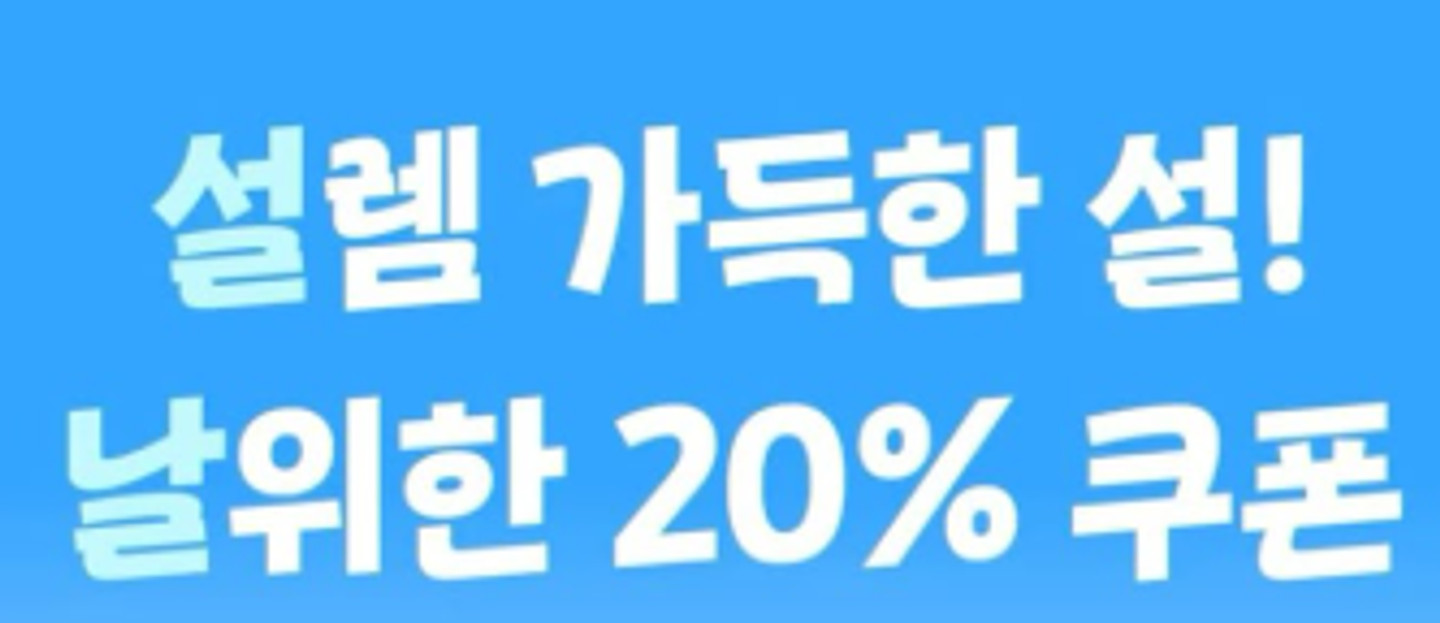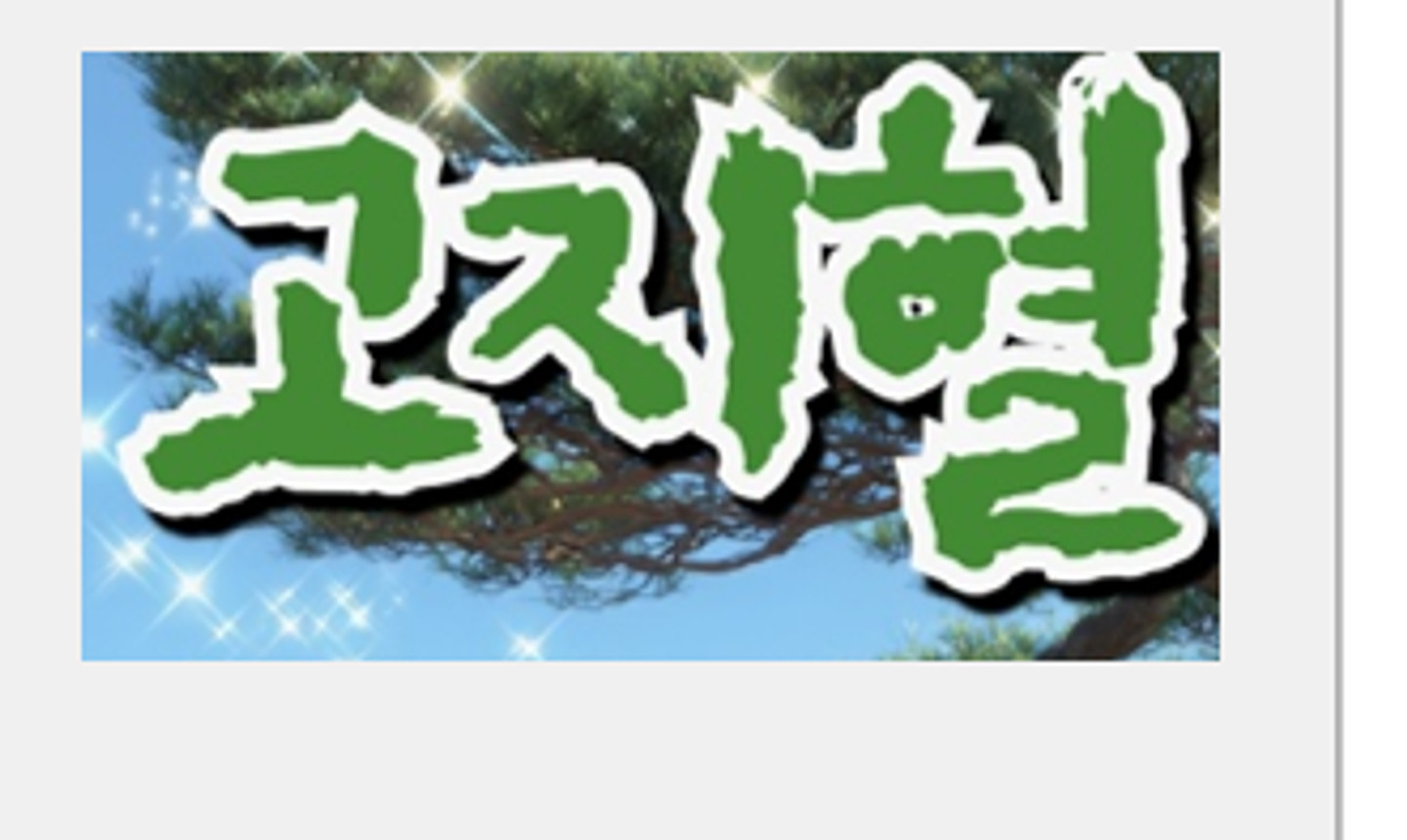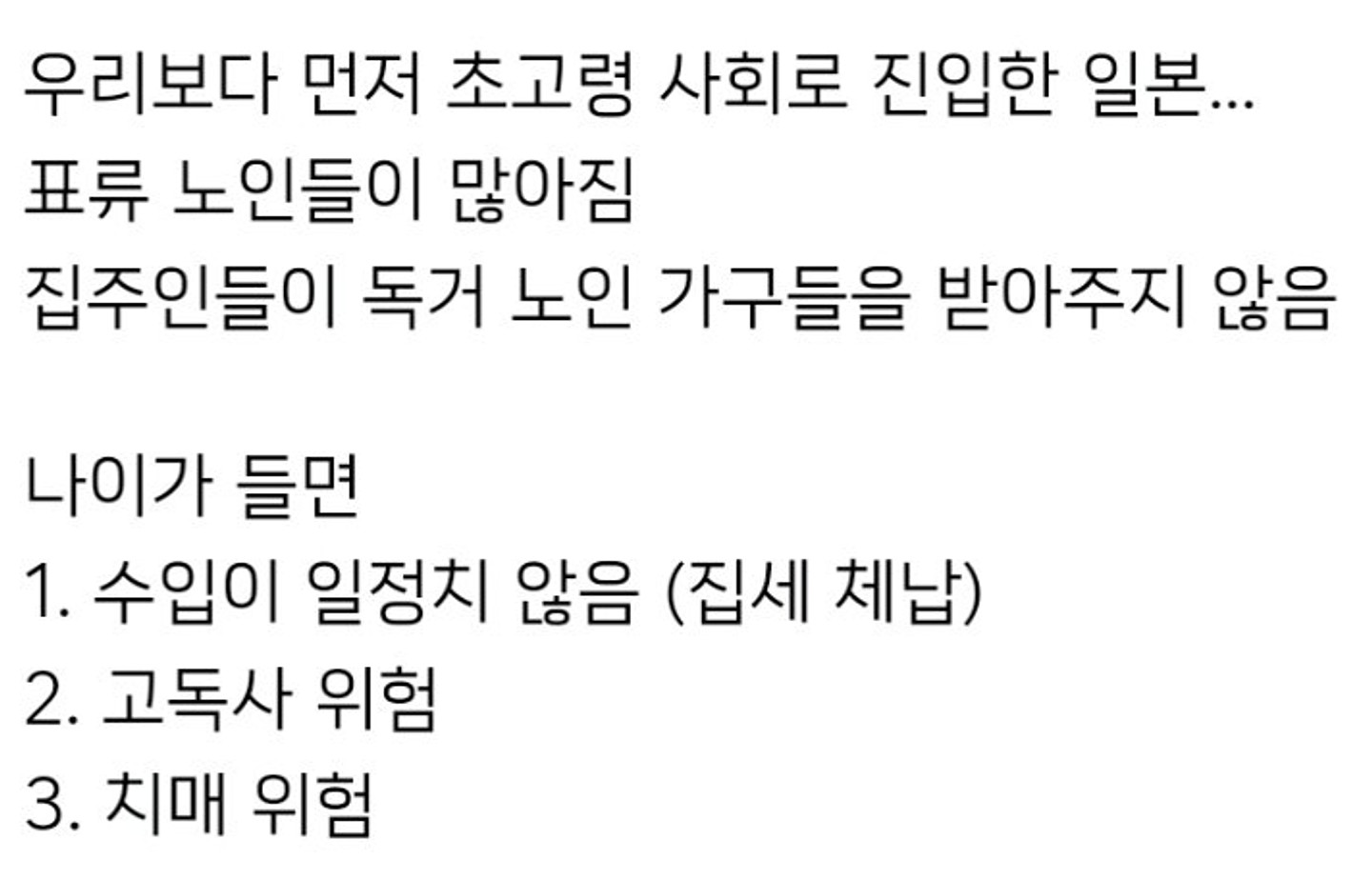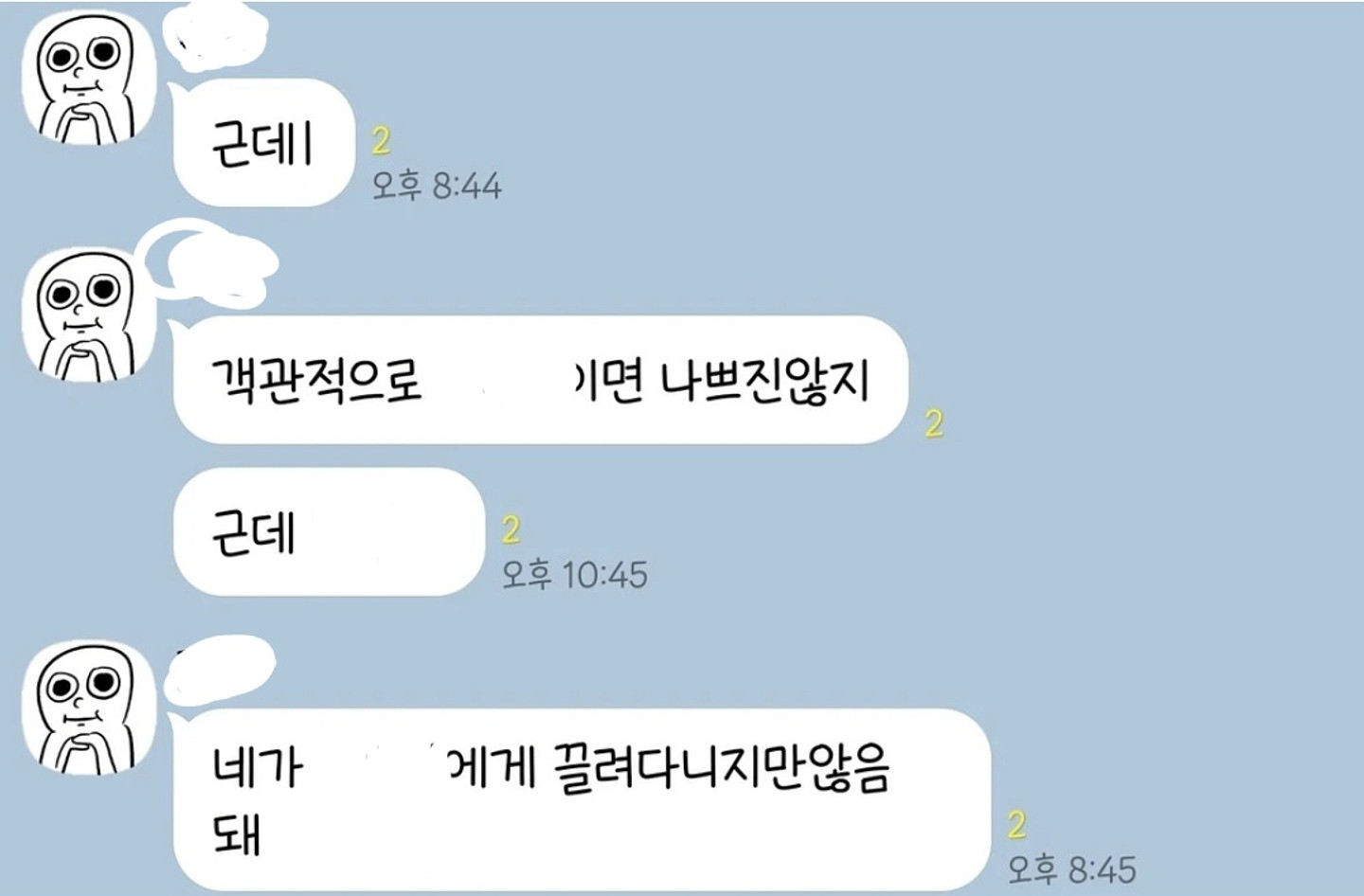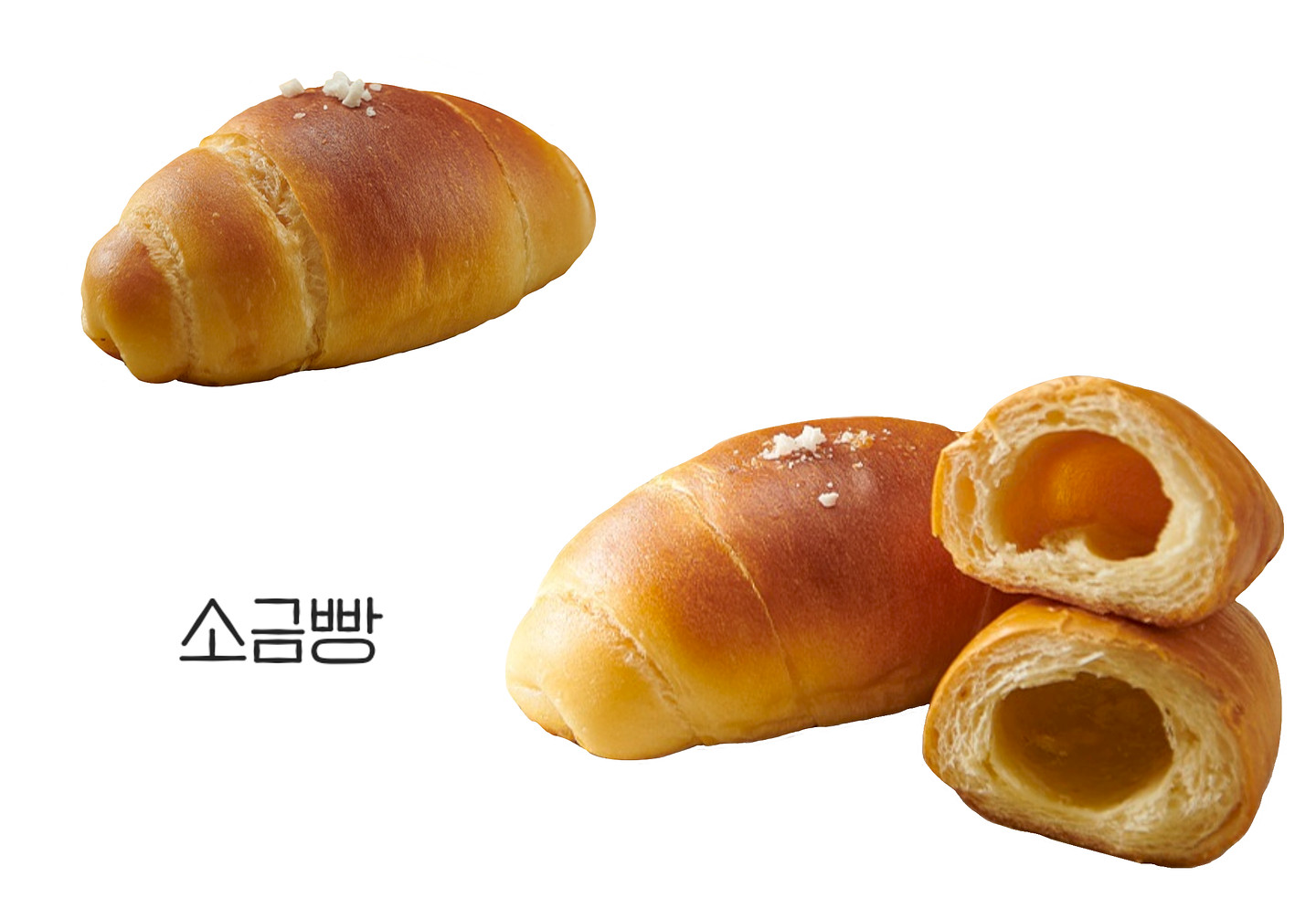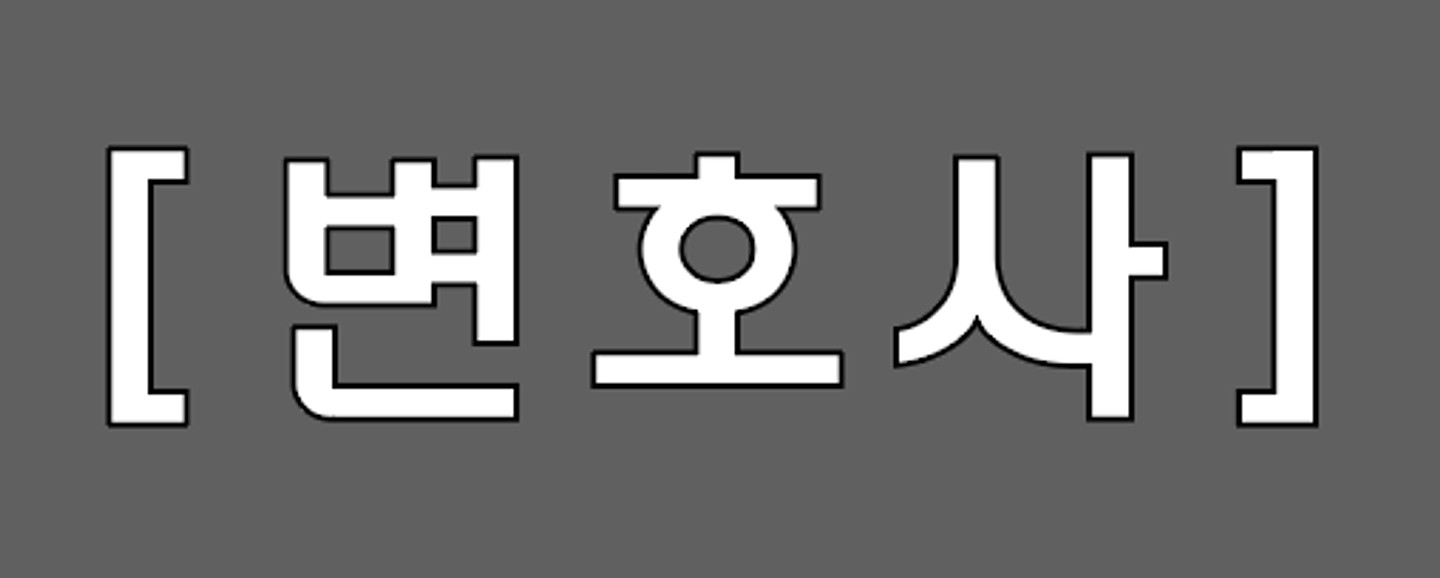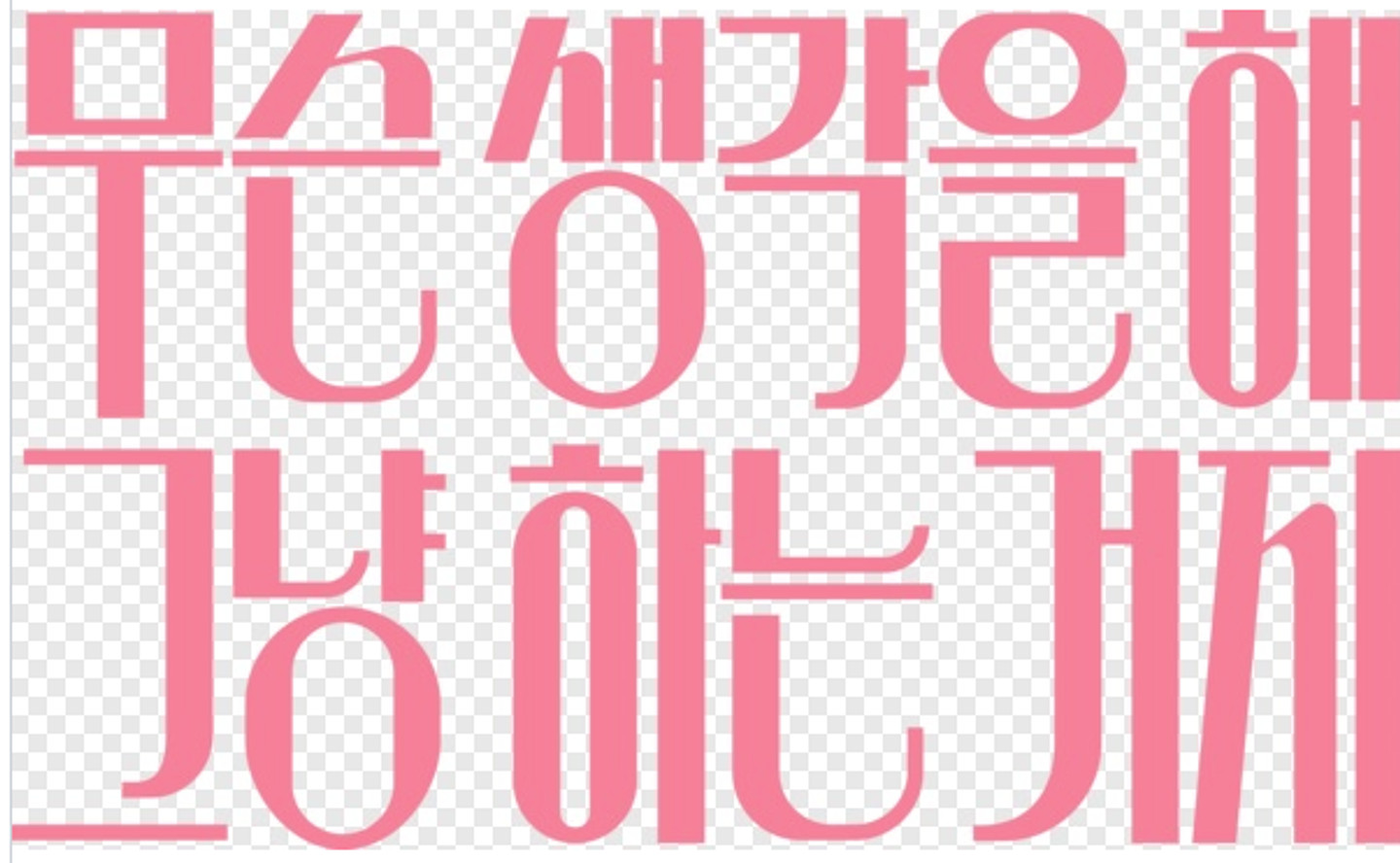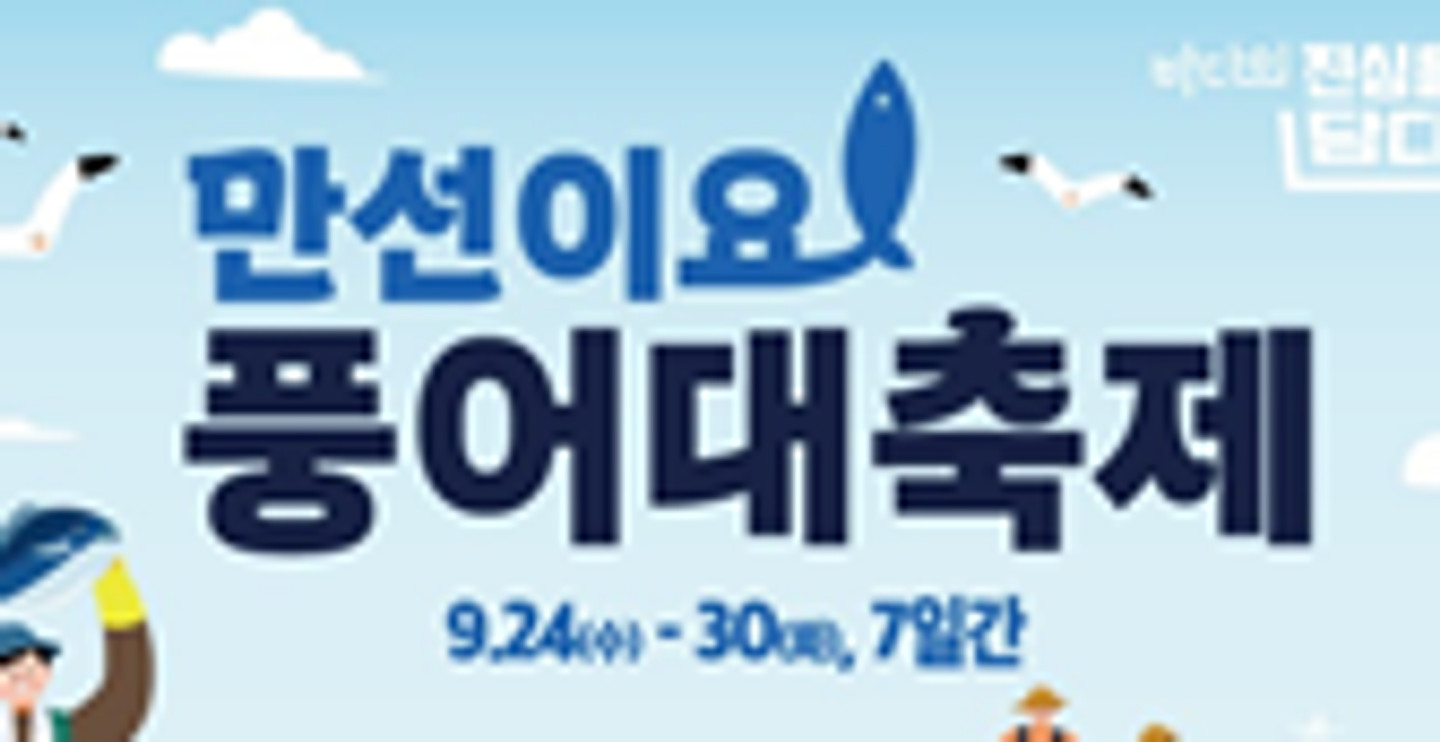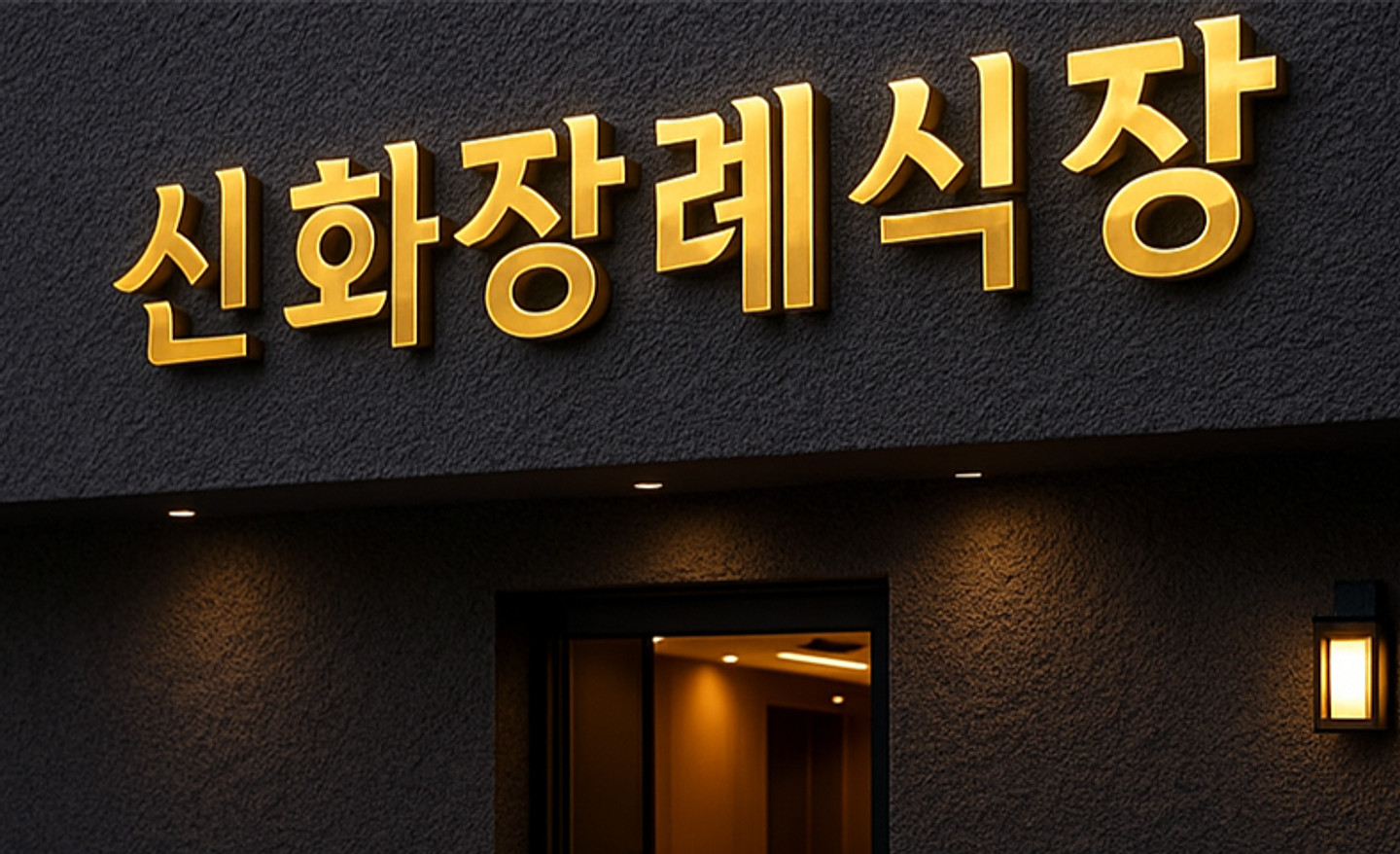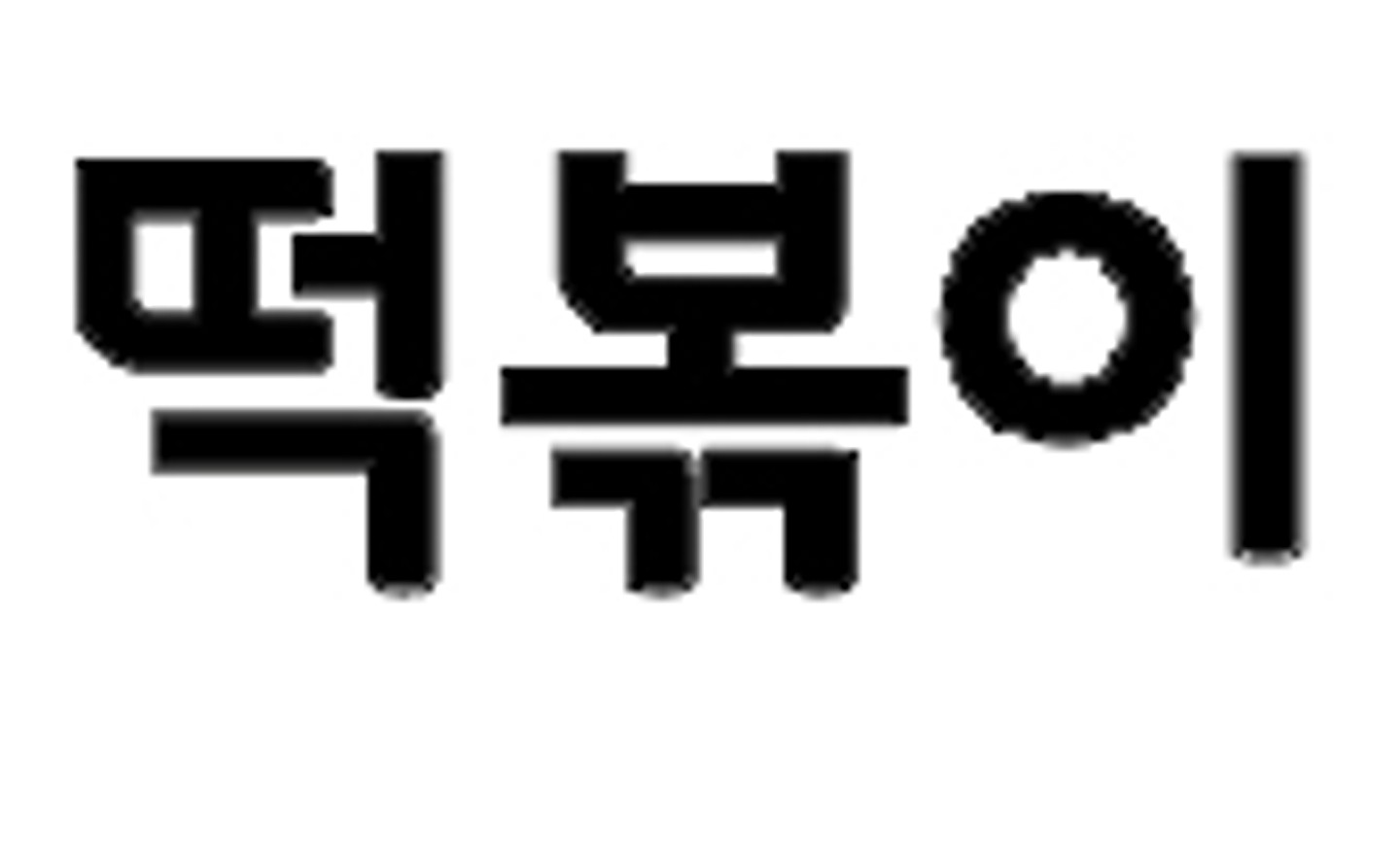
저거 무슨폰트일까요??
저 리을 어디서 많이 봤는데 기억이 안나요 ㅠ
본문 폰트가 궁금해요
어떤 폰트인지 궁금해요
궁금패요
ㅔ발용
여기에 사용된 폰트 2가지 알 수 있을까요ㅠㅠ
민음사 유튜브 세문전 독서클럽에 나온 자막 폰트를 찾고 싶습니다..! 아무리 검색해도 나오지 않아서.. 혹시 아신다면 도움주시면 정말 감사할 것 같아요!
폰트가 어떻게 될까요..?!!
이 폰트 뭔가요..
이 폰트를 찾고싶어요ㅠ 정확히는 S에 쓰인 폰트요!!
이 폰트가 뭔지 아시나요?!
이 폰트 아시는 분 있을까요?ㅜㅜ 찾아봐도 잘 모르겠네요
이거 몬지 아실까요? ㅎㅎ
이거무슨폰트인가요ㅠㅠ 초보라 잘모르깃어요..
이 폰트 뭔가요?? 알려주시면 감사드리겠습니다!
이 글씨체 알수있을까요
이 폰트 아시는분 ㅠㅠㅠㅠ
이 폰트 찾아주실분 ,,! 「 특?징 」 // ‘ 잡 ‘ 글자의 ㅂ이 막혀있ㄷㅏ . // ㅎ의 윗부분이 약간 대각선이다 . // 동글동글하다 . // 온글잎 @@@체 이다 ( 3글자예요 ! ) 찾아주시는분 천사 🥹
먼작귀 공식 만화에서 사용되는 폰트가 뭔지 궁금합니다 아무리 찾아도 안나오네요..
이 폰트 무슨 폰트인가요?
이서윤체랑 비슷한데 달라요 ㅠㅠ 무슨폰트인지 아시는분계실까요??
이 폰트 무슨폰트인가요??
이 폰트 뭘까요ㅠㅠ
혹시 아시는 분 있으실까요...
이 폰트뭔지 알고싶어요
스트로크 적용한 것 같긴한데 무슨 폰트인가요?
'위한'이 똑같아서 손글씨가 아닌 폰트같은데 뭐죠
화질이 좋지 않지만 혹시 아시는 분 계실까요ㅠㅠ
여기 쓰인 폰트 어떤 폰트인지 궁금해요~
사용된 폰트 궁금합니다
이 글씨체 뭘까요???
찾아주세여 ㅠㅠ
이 폰트 알수 있을까요?
이 폰트 이름이 뭘까요?ㅜㅠㅠ 이틀째 찾고있는데 정확히 일치하는 폰트를 못찾앗어요....
폰트 알려주실 수 있나요?! 감사합니다.
롯데마트 엘레베이터에 있던 말복 포스터입니다.
이폰트 이름좀 알려주세요
알려주세요ㅜ감사합니다
이 폰트 궁금합니다!!
폰트 정보 아시는 분!!!
이거 뭘까요..? ㅜㅜ
제발요..
이거 폰트 아시는분??ㅜㅜ
니디걸 오버도즈 게임입니다 폰트가 궁금해요
이 폰트가 무슨 폰트일까요?? 김태균 해설위원 개인 유튜브 작년 초 숏폼 영상들 보면 나오던 상단 자막이던데
어떤 폰트인지 아시는 분!!
이거 영문이랑 한글 무슨 폰트인가요~?ㅠㅠ